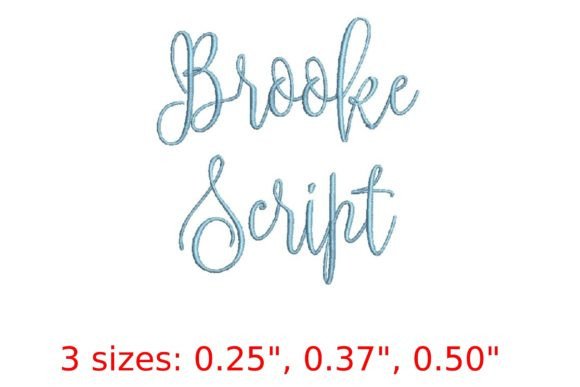
Brooke Script Embroidery Font
Brooke Script Embroidery Font — це елегантний, ручно створений шрифт у форматі PES, спеціально розроблений для машинної вишивки. З його плавними з’єднаннями, природними варіаціями товщини ліній та аутентичним «ручним» виглядом Brooke відразу виділяється серед типових скрипт-шрифтів для вишивки. Він ідеально підходить для вишивки імен, монограм, весільних прикрас, подарункових речей та брендування преміум-сегменту — завдяки продуманій балансуванню між читабельністю та художнім виразом.
Якість збірки та технічні деталі
Шрифт надається у форматі PES (з підтримкою інших форматів через конвертери), включає повну латиницю (A–Z, a–z), цифри, основні пунктуаційні знаки та спеціальні символи. Кожен символ оптимізований для стабільної вишивки: щільність стібків — 35–45 стібків/см, кут нахилу стібків адаптований під кривизну ліній, а перехідні елементи (напр., з’єднання літер) мають плавні векторні криві без розривів або надлишкових стібків. Шрифт проходить тестування на різних вишивальних машинах (напр., Brother PR-series, Janome MB-series, Tajima), забезпечуючи високу надійність навіть при розмірах від 60 до 250 мм.
Для кого найкраще підходить цей продукт?
Brooke Script ідеальний для професійних вишивальників, малого бізнесу (напр., власників студій весільних аксесуарів, дитячих товарів або преміум-одягу), а також для дизайнерів, які створюють цифрові шаблони для продажу. Також підходить для хобі-користувачів з базовим досвідом роботи з PES-файлами, оскільки шрифт не вимагає ручної редагування — всі літери гармонійно поєднуються при автоматичному наборі тексту в програмах типу Wilcom E4, Embrilliance або Hatch.
Як це порівнюється з конкурентами
На відміну від популярних альтернатив, таких як 'Lavanderia Script' (який має більш жорстку геометрію) або 'Alexandra Script' (з надмірною кількістю декоративних завитків), Brooke Script пропонує урівноважену комбінацію читабельності та елегантності без зайвого навантаження. Він має ширшу міжлітерну відстань порівняно з 'Brielle Script', що значно зменшує ризик перекриття стібків при вишивці довгих слів, і водночас забезпечує більш натуральну ритмічність, ніж у 'Savannah Script'.